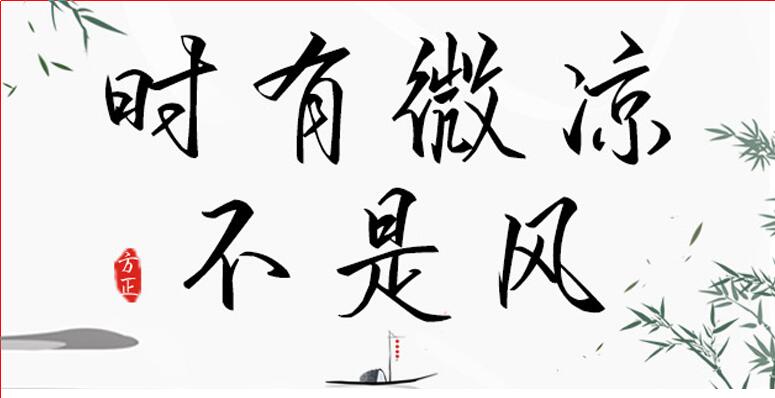
時(shí)有微涼不是風(fēng)這款字體用筆瀟灑從容,粗細(xì)變化,自然隨意,重心平穩(wěn),韻味悠長。適用于文藝類的書刊、文化類宣傳設(shè)計(jì)、綜藝字幕、品牌廣告和產(chǎn)品包裝設(shè)計(jì),以及社交網(wǎng)絡(luò)的個(gè)性化用字。歡迎喜歡這款字體的朋友下載收藏。